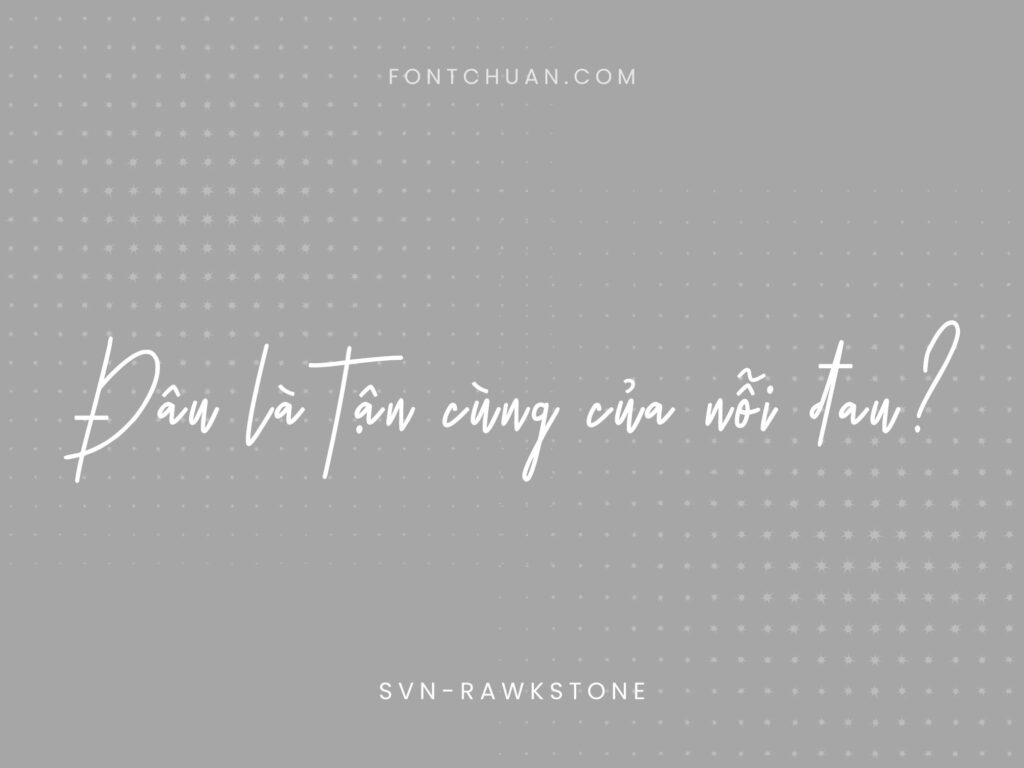
Font SVN Rawkstone Việt Hóa
Tác giả Font: Flycatcher Design
Font SVN Rawkstone là phiên bản Việt hóa của kiểu chữ Rawkstone, được thực hiện bởi STYLEno.1 Fonts. Rawkstone là một bộ đôi font chữ mang phong cách chữ ký ấn tượng, được thiết kế bởi Flycatcher Design. Bộ đôi này bao gồm hai phong cách chữ: một kiểu chữ viết tay tự nhiên và một kiểu chữ sans-serif đơn giản, tạo nên sự kết hợp hoàn hảo cho các thiết kế đa dạng. Rawkstone nổi bật với các nét chữ mềm mại, uyển chuyển, mang đến vẻ đẹp thanh lịch và hiện đại. Font này bao gồm đầy đủ các ký tự chữ hoa, chữ thường, chữ số và dấu câu, hỗ trợ đa ngôn ngữ. Font này phù hợp cho nhiều mục đích sử dụng khác nhau như thiết kế logo, tiêu đề, bao bì sản phẩm và các ấn phẩm truyền thông.
SVN Rawkstone lý tưởng cho các dự án thiết kế yêu cầu sự thanh lịch và chuyên nghiệp, như thiết kế logo, tiêu đề, bao bì sản phẩm và các ấn phẩm truyền thông. Các ngành nghề như thiệp cưới, giáo dục và bất động sản có thể tận dụng font này để tạo điểm nhấn trong thiết kế. Ngoài ra, font cũng thích hợp cho các sự kiện như Tết, Valentine, Sinh nhật và các lễ hội khác.